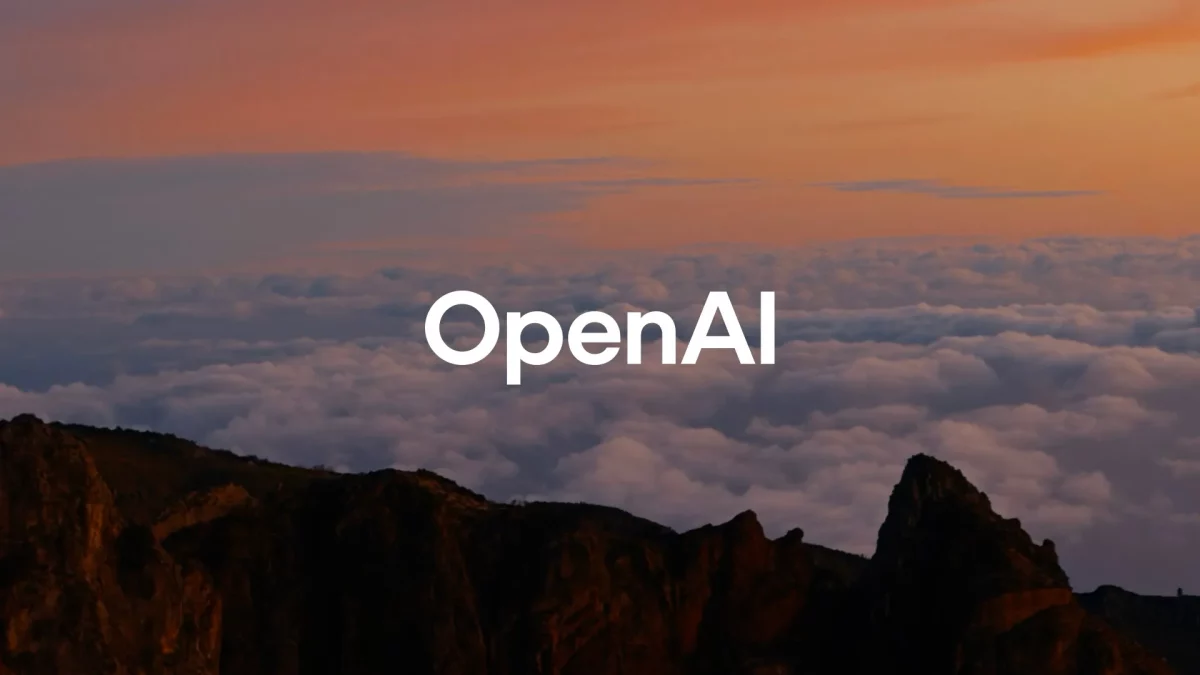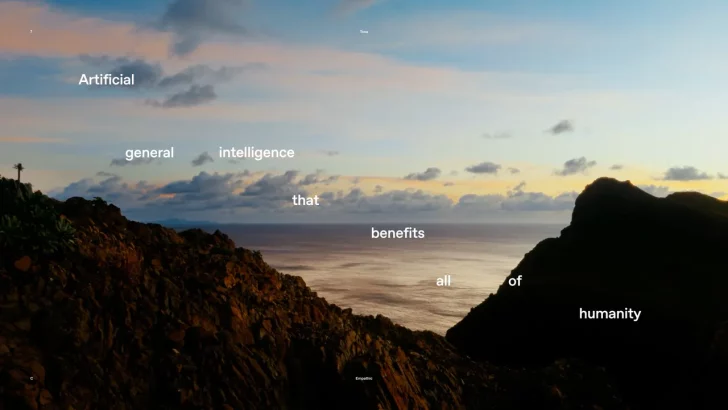
OpenAI, yapay zekâ sektöründeki hızlı büyümesini sürdürerek önemli adımlar atmaya devam ediyor. 2015 yılında kâr amacı gütmeyen bir araştırma kuruluşu olarak kurulan şirket, 2022’de ChatGPT’yi piyasaya sürmesiyle büyük bir çıkış yakaladı ve o zamandan beri sürekli yenilikler sunuyor. Bu yıl ise OpenAI, daha bütüncül bir strateji benimseyerek ilk kez bir marka yenileme sürecine giriyor.
Liderliğini Korumak İsteyen OpenAI, Yeniden Markalaşma Sürecinde
Son bir yıl içinde büyük bir dönüşüm geçirerek daha kâr odaklı bir yapıya evrilen OpenAI, yapay zekâ alanında yeni modeller ile özellikler tanıtma konusunda iddialı bir duruş sergiliyor. Şirket, Yapay Genel Zekâ (AGI) hedeflerine vurgu yaparken gelecekte aracıların (AI agents) büyük bir yenilik olabileceğini öne sürüyor. DeepSeek’in başarısının ardından çalışmalarını hızlandıran OpenAI, şimdi tamamen yenilenmiş bir kimlikle karşımıza çıkıyor. Wallpaper ile yapılan bir röportajda, bu dönüşümün detayları ve şirketin yeni stratejisi ele alındı.
OpenAI, marka kimliğini yenileyerek daha modern ve ferah bir görünüme kavuştu. Şirket, yeni bir yazı tipi seçerken logosunu güncelledi ve renk paletinde değişiklikler yaptı. Bu tasarım değişiklikleri, OpenAI’ın insan merkezli ve daha doğal bir kimlik oluşturma hedefiyle şekillendirildi. Yeni marka kimliğinin arkasındaki isimler ise şirket içi tasarımcılar Veit Moeller ve Shannon Jager.
Yenilenen marka kimliğinde en dikkat çeken unsurlardan biri, özel olarak tasarlanan OpenAI Sans yazı tipi oldu. Bu yazı tipi, geometrik hassasiyeti yumuşak bir dokunuşla harmanlayarak dengeli bir estetik sunuyor. OpenAI kelimesinin bir parçası olan bu tasarımın en etkileyici yanı, dış hatlarının kusursuz yuvarlak formda olması ancak iç kısımlarının düzensiz dokusuyla markaya daha insani bir görünüm kazandırması. OpenAI, sektördeki konumunu güçlendirmeye odaklanırken bu ilk marka yenileme adımı, şirketin yenilikçi ve heyecan verici gelişmeler sunma hedefini daha da pekiştiriyor.